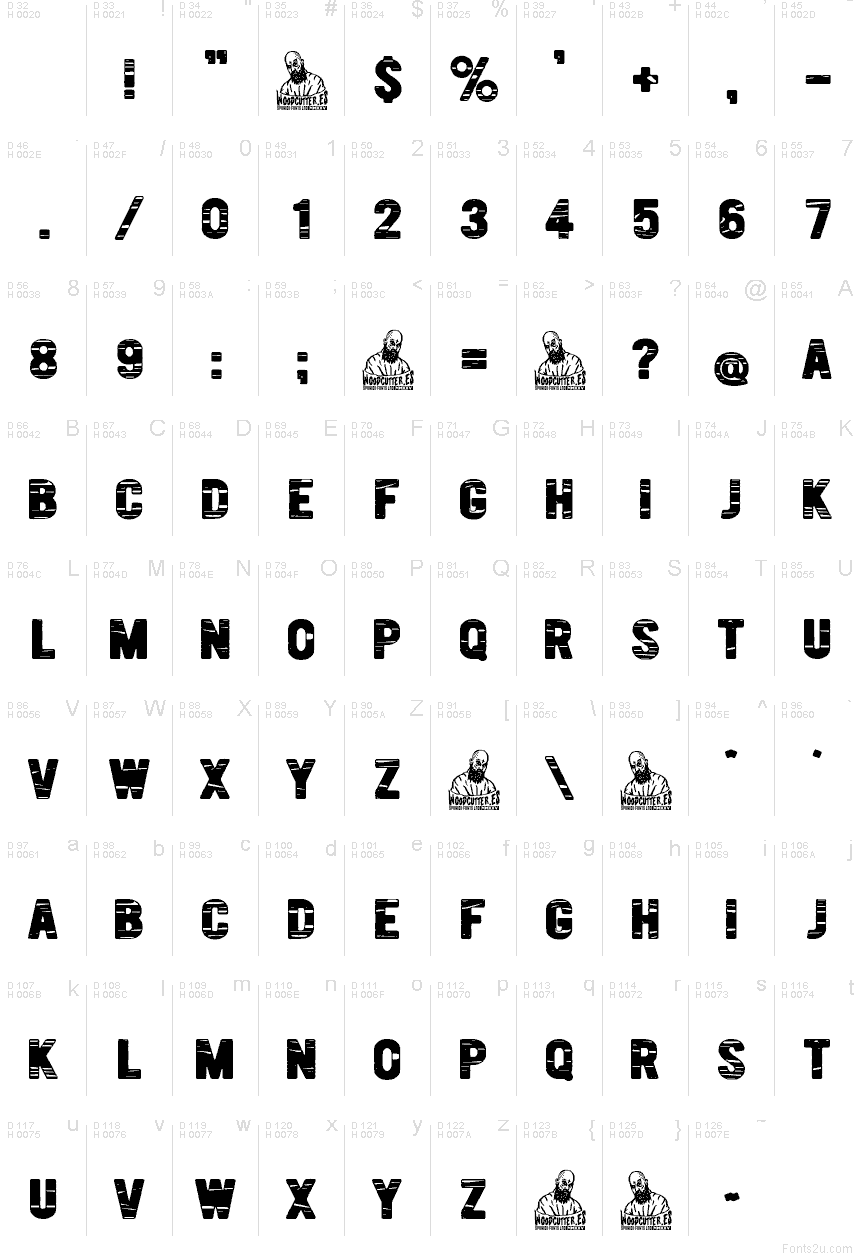
Wood Chaos de Woodcutter Manero est une police display gratuite au style gravure sur bois, composée de lettres lourdes et massives, marquées par des incisions horizontales brutes. Les formes semblent sculptées directement dans du bois brut ou estampées à partir de planches vieillies, avec des arrondis intérieurs et des éclats qui confèrent à l'ensemble une texture forte et un caractère indomptable.
Elle est idéale pour les affiches, les titres de films d'horreur ou comédies, le branding d'événements rustiques, les logos de jeux vidéo et les packagings qui recherchent un rendu brut et artisanal plutôt qu'un fini trop lisse. En tant que police gratuite, elle est parfaite pour des titres, des cartons de présentation ou de grands monogrammes, où ces rayures marquées donnent, même à quelques lettres, l'allure d'une enseigne en bois usée.